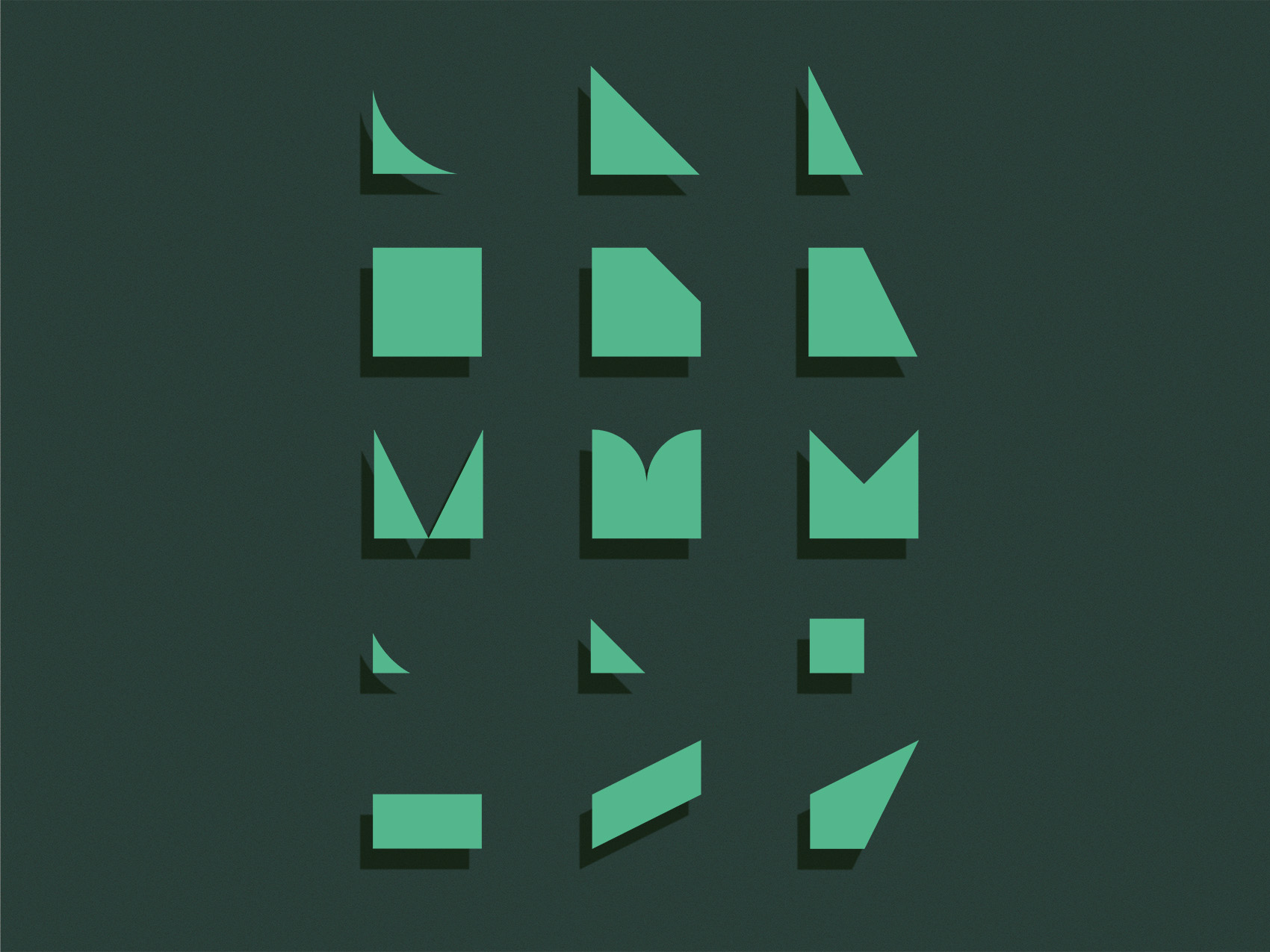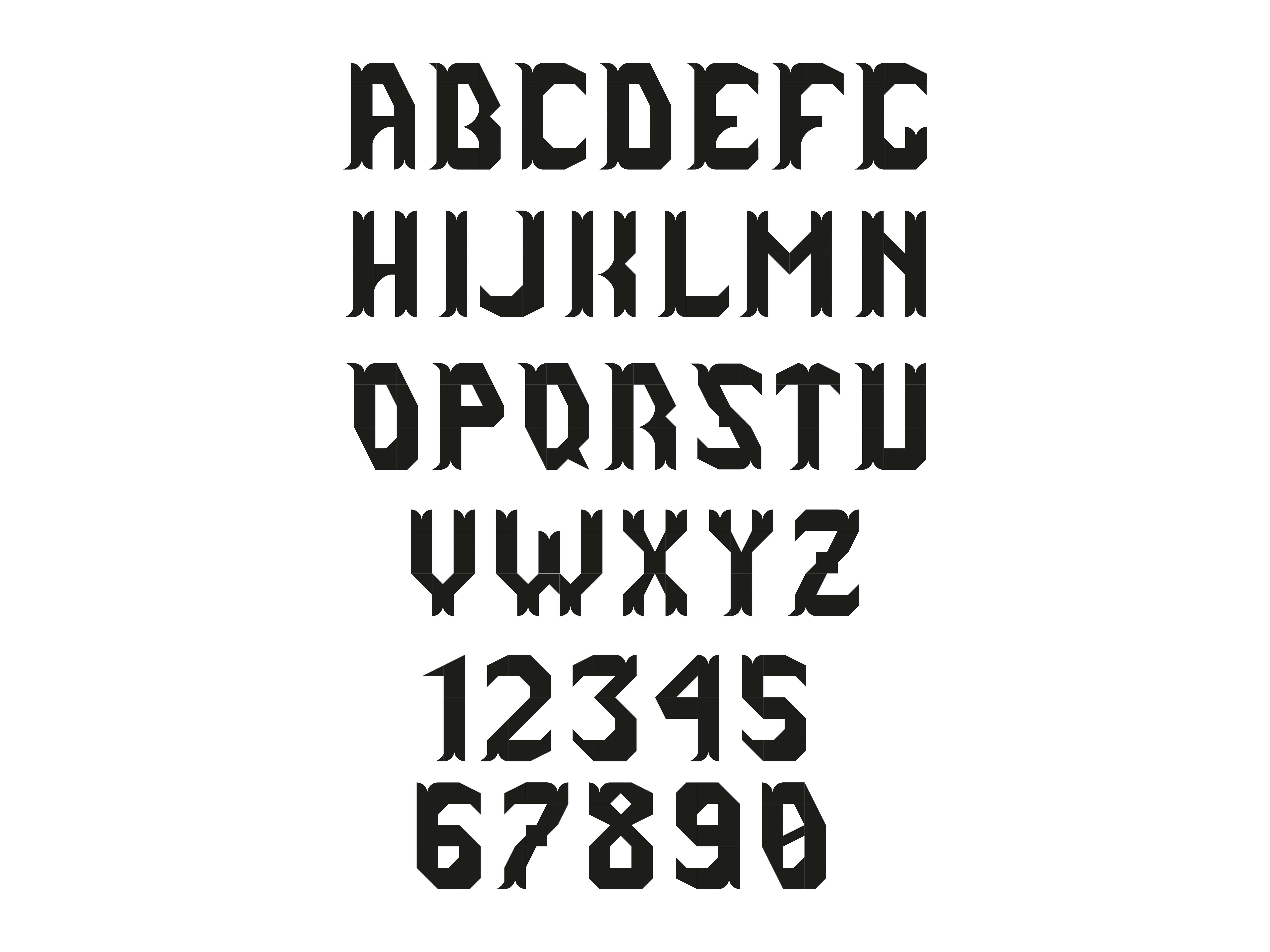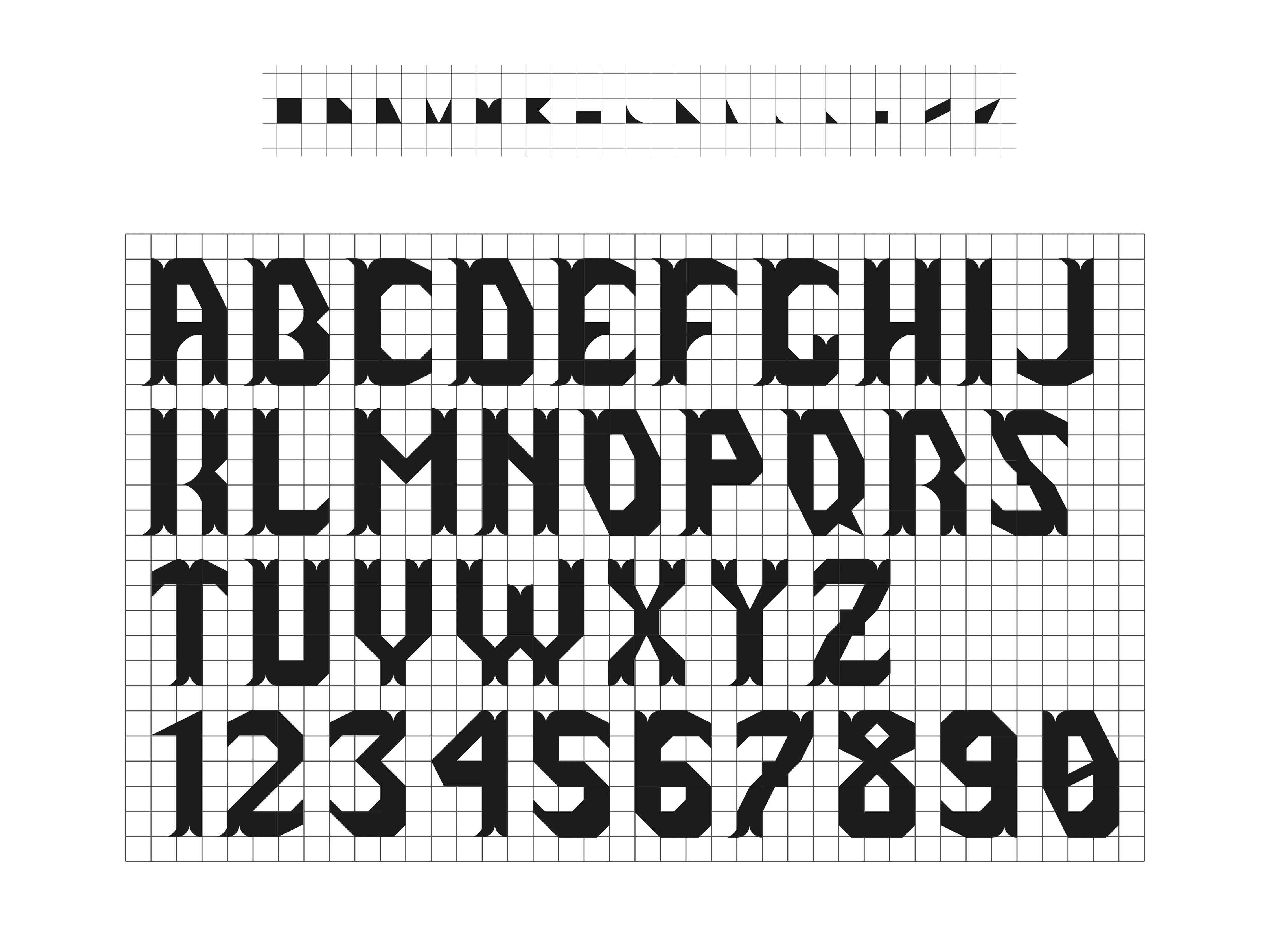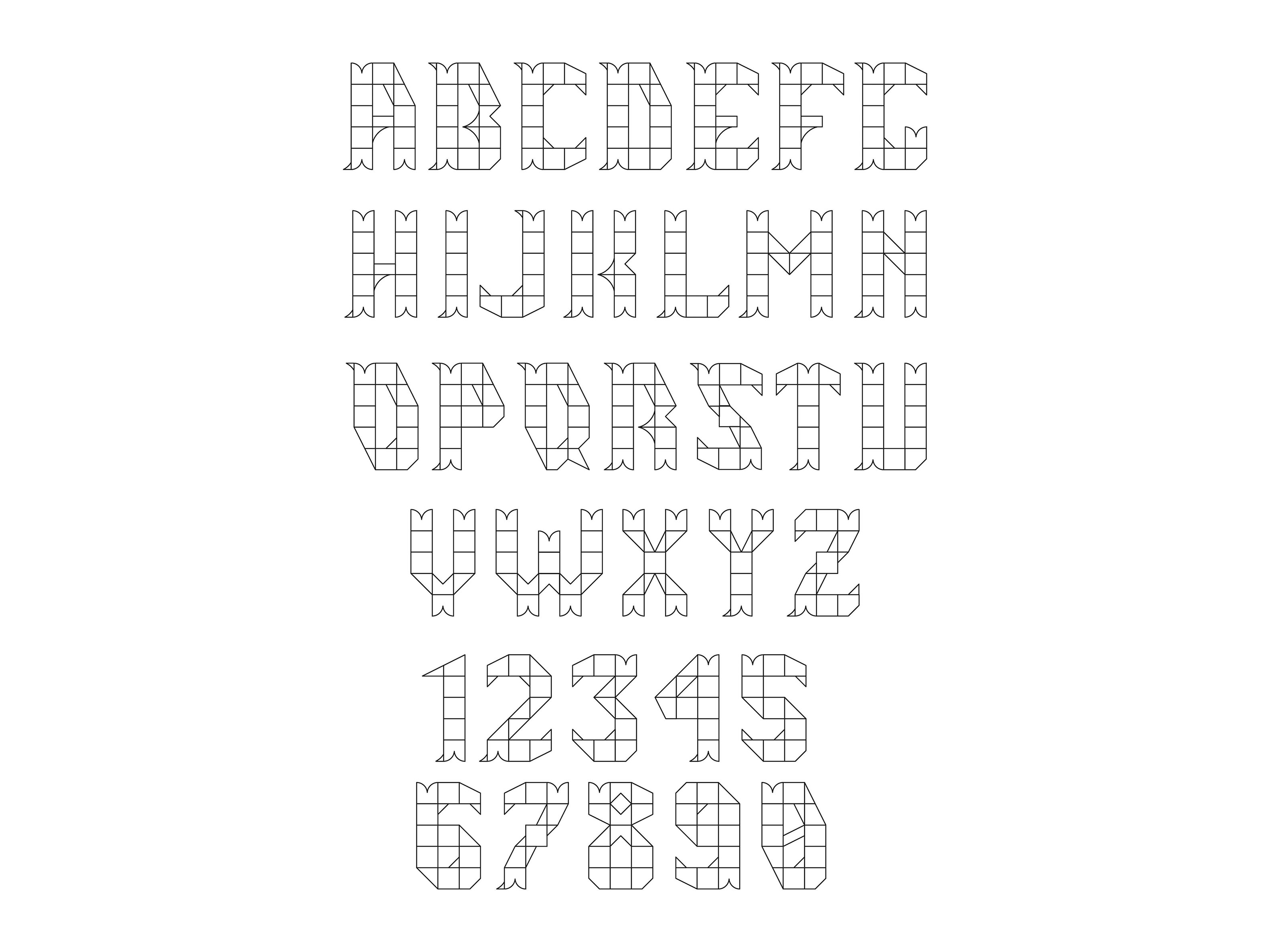
Apothecary font modulare
Apothecary è una font modulare sviluppata con una serie di moduli selezionati per raggiungere il risultato finale di un tuscan dalla modulazione calligrafica.